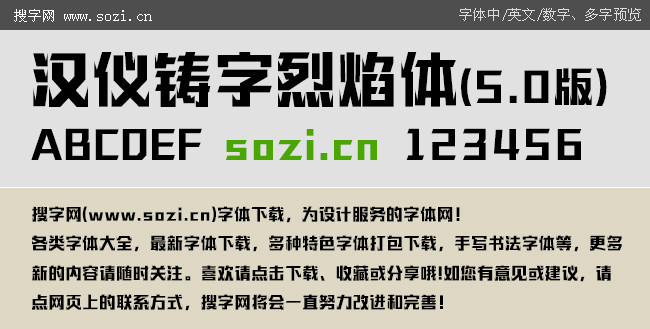
漢儀鑄字烈焰體5.0
搜字網(wǎng)提供一款漢儀鑄字烈焰體5.0中文字體下載,漢儀鑄字烈焰體是漢儀字庫設計的一款帶有火焰元素的藝術字體,火焰給人溫暖,還有欣欣向上的含義,這款字體在文字的末端抬筆的地方就像是火焰一樣一直向上,而且還做出了尖端處理,不僅有火焰的感覺,還有一種鋒利的感覺,能夠適用于藝術設計、包裝印刷、海報設計、圖形設計等領域。(如需要商用請聯(lián)系漢儀字庫購買版權)